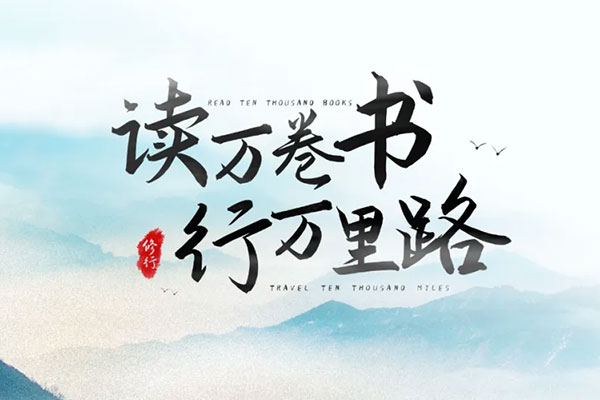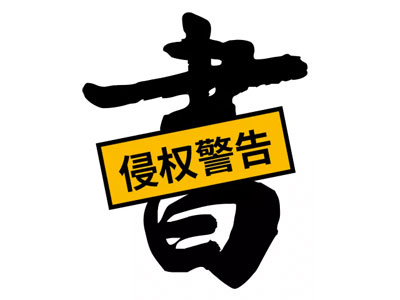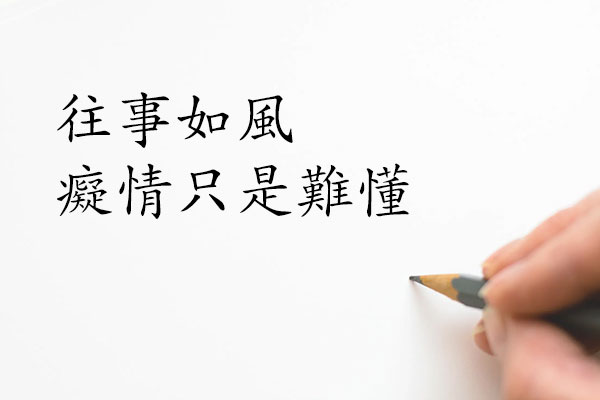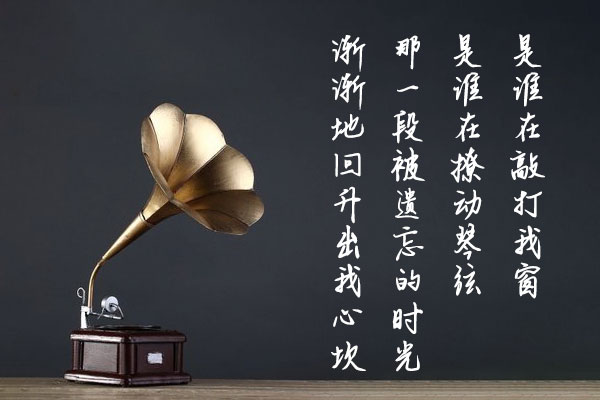
想要不侵权?收下这篇可能是最全面的书法字设计指南!
@研习设K先生 :中国文化有五千年的历史,汉字在这其中有着至关重要的作用。汉字从甲骨文开始,发展至今已有三千多年,是世界上最古老的文字之一,也是唯一传承至今的文字。随着历史的演变,先后经历了甲骨文、金文、大篆、小篆、隶书、楷书、行书、草书等字形变化,每种书体都有其很重要的艺术价值与历史意义。
在现代设计中,应用最广泛的字体之一就是行书字体,很多人会称为书法体。其实单纯就行书字体而言,称其书法体还是比较片面,有的人把历史长河中出现的文字都称为书法字体,有的人则认为书法字可以用篆体,隶书,楷体,行书,草书,这五种书体来概括,这里我们不用深入的追究如何定义书法字,我们只需要了解每个文字的历史和行书文字在现代设计中的应用就可以了。首先我们从文字起源讲起。
文字的历史
传说文字的起源是用结绳记事来传播信息。
想要不侵权?收下这篇可能是最全面的书法字设计指南!
△ 结绳记事
还有个说法是八卦说。
△ 八卦说
△ 河图洛书说
△ 仓颉造字说
当然,前面都是传说,大家感兴趣的可以上网搜寻一下,还是很有意思的,而真正的历史就要上演了。
1. 半坡陶符与甲骨文
最开始是半坡陶符和甲骨文:
甲骨文是中国最早的汉字资料,甲骨文,是雕刻在兽的骨头或者甲片上的象形文字,但也有一些学者认为,半坡陶符是中国最早的文字源头,我们不用纠结到底从谁开始的,这个只需要了解一下就行了,那看看在它们之后是什么文字呢?
钟鼎文也称金文,是甲骨文的延续与发展,出现于商末时期,到周朝时到达顶峰,秦汉时期开始衰弱。周朝时期,占卜已经不流行了,甲骨文也就慢慢消亡了,用于铭刻的钟鼎文逐渐取代了甲骨文成为汉字的主要形态。因为文字是铸刻在以鼎为代表的礼器和以钟为代表的乐器上,所以叫「钟鼎文」。因为当时的铜也叫金,所以也叫金文。
金文在文字结构和用字上与甲骨文基本相同,区别就是金文是铸在青铜器上,与用刀刻的甲骨文在风格上还是有差异的,甲骨文一般线条比较纤细,金文更多是比较圆润肥厚的笔画。
2. 大篆
篆书是中国书法五体之首,是大篆和小篆的统称,大篆为西周时普遍采用的字体,广义的大篆指的是小篆以前的书写文字,包括甲骨文、金文等。
3. 小篆
小篆又称「秦篆」。在秦始皇统一中国之后,宰相李斯在大篆的基础上简化,并取消了其他六国的异体字,创造出统一规范的汉字书写形式,这次文字改革是中国历史上第一次有系统地将文字的书写标准化,小篆一直延续到西汉末年,才被隶书取代。
大篆与小篆对比下,还是很容易辨认的,像甲骨文、早期的金文,有些字外形会明显带有不规则的感觉,就是大篆;秦代的小篆,把每个字写的都很匀称,笔画圆通,跟大篆明显的不一样。
由于篆书笔画复杂、外形独特、不易模仿,因此在古时篆书被选为刻公文印章的字体。
4. 隶书
隶书,形成于秦,成熟与汉,相传秦始皇新政期间,政务繁忙。小篆不便于速写,费时费事,影响工作速度和效率。然后有个叫程邈的人,就开始钻研文字替代篆书,终于创造出比小篆更易书写的隶书,免去了他的罪并提升为御史,由于程邈的官职很小,属于「隶」,所以人们就把他编纂的文字叫隶书。
隶书结构扁平、工整,横画长,而直画短,撇、捺等笔画为美化而向上挑起,轻重顿挫富有变化,非常漂亮。隶书是汉字演变史上重要的转折,它打破了以往的书写传统,逐步奠定了楷书的基础,同时,它还派生出草书、行书等其他书体,是中国文字发展史上的又一次重大改革。
隶书极大地减少了篆书文字的笔画,让书写变得简单和快捷。隶书的这种基本特征直到今天都得以保留。比如说,我们字库里很多关于隶书的字体,大家可以打出来观察下笔画特征。
还有现在国外唐人街的招牌,香港街头还会沿用隶书体来作为招牌字体。
5. 楷书
楷书萌芽于西汉,魏晋以后开始盛行,楷书从隶书演变过来,它把隶书的波势挑法变得平稳,把隶书的柔和的弯变成了硬钩,把隶书的平直方正变成了长方形,成为直到现在都十分通行的字体。楷书的字体端正,结构严谨,笔画工整,便于阅读,已成为现代汉字的标准字体。我们小学课本经常能看到楷书的文字。
推荐一些字库当中常用的楷书字体:
6. 草书
草书是在隶书的基础上演变出来的字体,它的特点是结构简单,笔画相连,草书的出现顺应了文字简便易写的要求,尤其是在社会变革和文化发展期间,文字应用频繁,带着强烈个人色彩的简笔和连体字出现了。由于草书一般难以辨识,实用性比较差,所以在设计中多将草书作为装饰图形来处理。
来欣赏一些带有草书的设计作品:
7. 行书
行书兴起于东汉,是介于草书和楷书之间的一种字体。它的书写速度比楷书快,但又不像草书那样难以辨识,行书的出现解决了楷书书写太慢和草书识别性差的问题,是在楷书的基础上适当加入草书的特点而形成的。有极大的实用价值,也是当今人们习惯用的字体。
天下第一行书之称的兰亭序,就是行书的代表作。
在悠长的历史长河中还有很多字体,比如说瘦金书,宋体,黑体等等,这里就不一一给大家介绍了。因为今天我们着重讲的就是行书字体,行书字形张弛有度,疏密得体,浓淡相融,笔画苍劲有力,也是设计师们经常会使用到的字体,接下来,我们看看行书字体在设计中如何应用。
应用领域
1. 包装
2. 网页banner
3. 海报
4. 招牌
5. 英文手写字
设计形式
1. 拆分笔画为主体
2. 与其他颜料结合
3. 行书字与英文字体的相互叠压